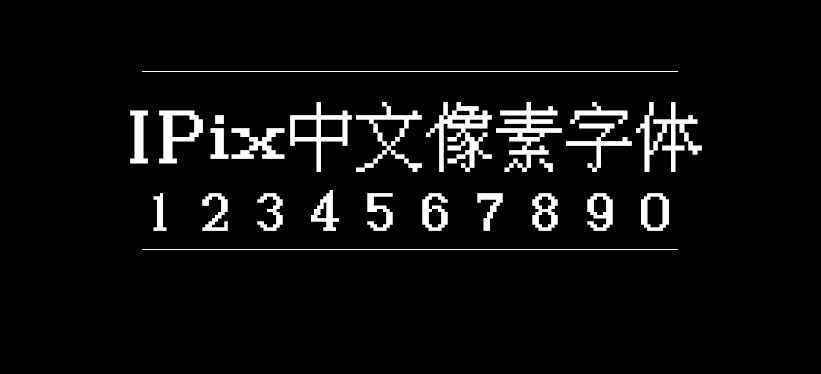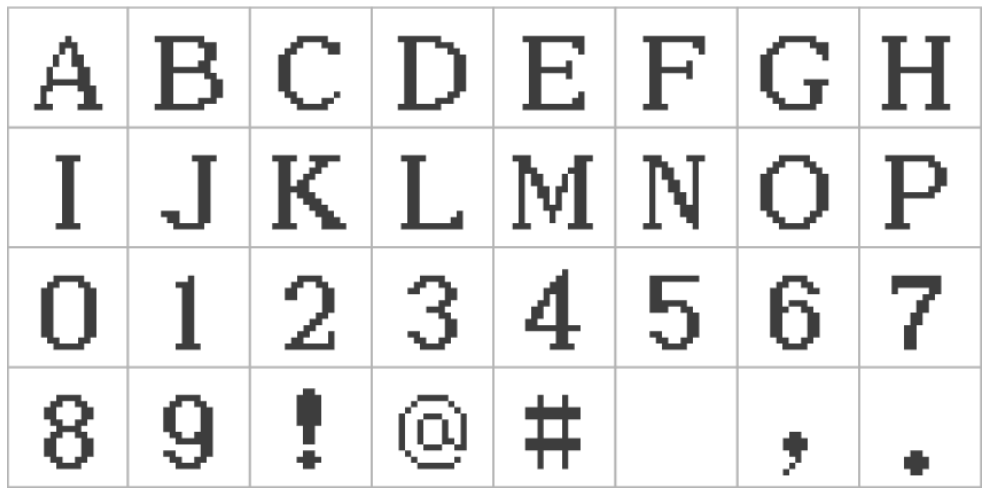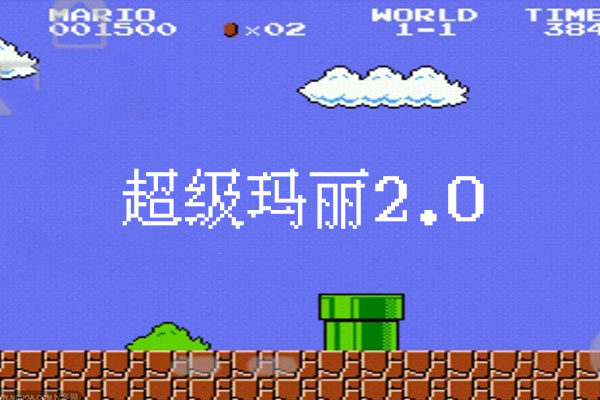
IPix中文像素字体
中文像素字体(IPix / Chinese Pixel Font)是一款风格比较特别的字体,这是一个像素中文字体,里面具有6000多个常用字 。特别适合复古游戏中使用,感觉好像回到了80年代那个红白游戏机的年代。 这是一个像素中文字体,里面具有6000多个常用字,其是使用HZK16字模制作。你可以用于商业用途,特别适合游戏项目中使用这个字体。